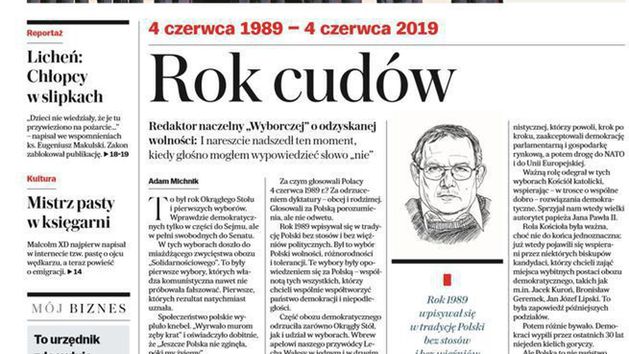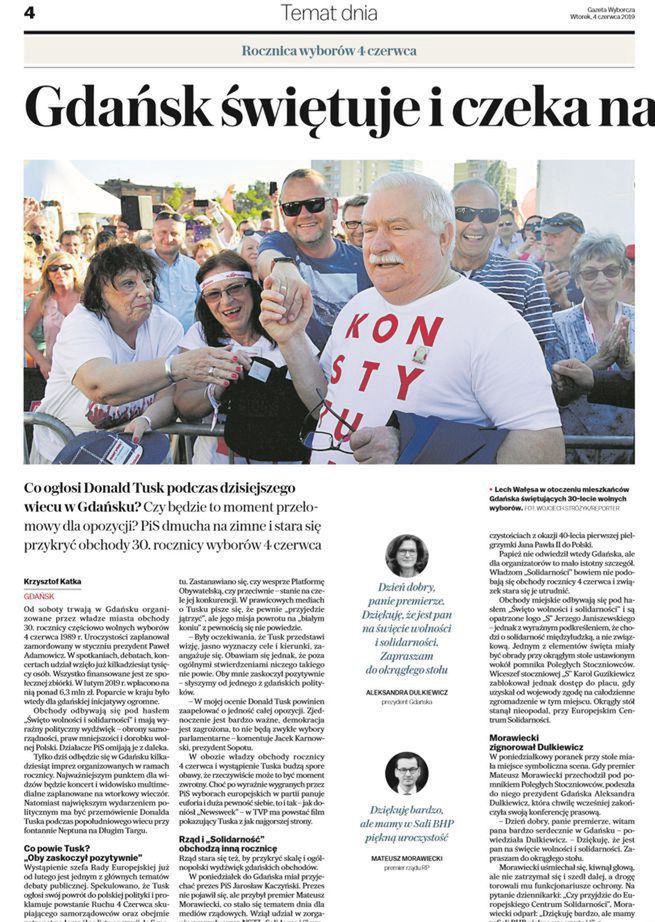
„Gazeta Wyborcza” świętuje w tym roku 30-lecie istnienia. W związku z tym odświeża makietę, której niemal nie zmieniała od 2006 roku. Nowy układ ma być nowoczesny, lżejszy i wprowadzać więcej „światła” na łamy. Zapewnić to m.in. nieco powiększona, prostsza czcionka, większe przestrzenie w projekcie poszczególnych stron oraz lepiej eksponowane fotografie, np. na drugiej stronie wydania. Dodatkowo autorzy komentarzy, felietonów i opinii będą przedstawiani rysunkowym portretem.
- W wymagających dla tradycyjnej prasy czasach nowa makieta wysokonakładowego dziennika to projekt wyjątkowy nie tylko na skalę polską. Zmiana układu i wyglądu wydań to znacznie więcej niż nowy projekt graficzny gazety – to także zmiana filozofii jej tworzenia oraz wyraźny, mocny sygnał, że wierzymy w nowoczesną, papierową „Gazetę Wyborczą” dopełniającą się z atrakcyjną ofertą cyfrową dziennika i dbamy o jej rozwój - mówi wydawca „Gazety Wyborczej” Jerzy Wójcik. - Nową „Wyborczą” ocenią oczywiście sami czytelnicy, ale jesteśmy przekonani, że jutro dostaną do ręki gazetę nowoczesną i klasyczną jednocześnie, a przede wszystkim przejrzystą i piękną.
Pojawią się „Temat dnia” i „Zdjęcie dnia”
Nowością będzie też „Temat dnia” - wyróżniony i najważniejszy zdaniem redakcji temat, który ma się przewijać przez kilka stron wydania dziennika. Obudowywany będzie różnorodnymi formami, np. komentarzami odredakcyjnymi, cytatami czy opiniami gości.
Na stronie drugiej gazety pojawi się natomiast „Zdjęcie dnia” - najważniejszy (zdaniem fotoedytora i wydawcy dziennika) kadr z poprzedniego dnia, obrazujący istotne wydarzenia w kraju lub na świecie.
Na dalszych stronach wprowadzonych zostanie sporo elementów dodatkowych - mniejszych form (jak komentarz czy rysunek), które będą miały za zadanie wspierać i obudowywać tematy wydania.
Nowa makieta ma być nowoczesna, dynamiczna, a wrażenie takie sprawiać będą m.in. tzw. rozkładówki, na których będą opierały się poszczególne strony. Wyraźniej graficznie będzie też zaznaczony główny temat każdego działu - tak by rzucał się w oczy czytelnikowi od pierwszej chwili, gdy ten przegląda gazetę (eksponowane miejsce, większy tytuł).
Druga część wydania to działy Opinie, Kultura, Nauka i Reportaż, w których więcej będzie dłuższych form dziennikarskich. Codziennie, oprócz sobót, na łamach dziennika pojawi się sekcja Poradnik, która będzie oferować praktyczne treści, użyteczne dla czytelników, np. informatory o zmianach w prawie, systemie emerytalnym bądź związane z edukacją. W czwartki Poradnik będzie miał charakter konsumencki, a w piątki zajmie cztery strony i w całości zostanie poświęcony tematyce zdrowotnej, zastępując wydania „Tylko Zdrowie”. W nowej makiecie zmieni się także wygląd tygodników „Duży Format”, „Ale Historia”, „Mój Biznes”, „Nasza Europa” i „Magazyn Świąteczny”.
Projekt makiety przygotował Jacek Utko, którego poprzednie projekty pięciokrotnie zdobywały nagrodę World’s Best Designed Newspaper i trzykrotnie European Newspaper of the Year.
- „Gazeta Wyborcza” będzie mieć szatę graficzną premium, odpowiednią do jakości swoich treści. Chciałem, aby jej makieta była bardziej spójna, by wszystkie sekcje i tygodniki wyglądały jak z jednej rodziny. Oczywiście, „Wyborcza” powinna też być nowoczesna i używać nowoczesnych rozwiązań graficznych, ale z konserwatywnym rysem, charakterystycznym dla prasy wysokiej jakości - wyjaśnia Utko.
Lokalne magazyny łączą się z „Co Jest Grane”, pojawiają się jedynkowe newsy
Od 7 czerwca zmienią się także lokalne wydania weekendowych magazynów „Gazety Wyborczej”. - Dzisiaj na okładkach dominują portrety. Nowy layout okładek da redaktorom większa swobodę i umożliwi lepszą ekspozycję tematów newsowych - mówi portalowi Wirtualnemedia.pl Mikołaj Chrzan, szef lokalnych redakcji „Gazety Wyborczej”.
Jak się dowiadujemy, wydawca połączy piątkowe magazyny lokalne z „Gazetą Co Jest Grane” w jeden grzbiet we wszystkich wydaniach poza Warszawą. - W ten sposób powstanie jeden obszerny, kompletny tygodnik z wydarzeniami, częścią featurową (większe formy) oraz informacjami kulturalnym i innymi, związanymi ze spędzaniem czasu wolnego. Przywracamy też opiniotwórczy charakter stronie drugiej: będzie z komentarzami, lokalnymi recenzjami i listami. Strona ta będzie miała także unikalny projekt graficzny - komentuje Mikołaj Chrzan. Dodaje też, że przygotowania z redakcjami lokalnymi obejmują nie tylko prace nad wdrożeniem nowego wyglądu stron, ale także wybór podejmowanych w piątki tematów.
Lokalne magazyny „Gazety Wyborczej” zmieniły się ostatnio w marcu ub.r. Zyskały wtedy nowe makiety, logotypy i tytuły, a na „jedynkach” pojawiły się portrety lokalnych bohaterów. Ostatnia strona była przeznaczona na rubrykę satyryczną. Zmiany miały służyć zdynamizowaniu wydań.
Zmiany zaprojektował Jacek Utko
To, że na 30-lecie wydania pierwszego numeru pojawi się nowa makieta, „Gazeta Wyborcza” zdradziła już w grudniu 2018 roku. Za projekt odpowiada Jacek Utko, który pracował nad nim od kilku miesięcy.
Utko projektował już szaty graficzne dla kilkudziesięciu dzienników na świecie m.in. dla „De Morgen”, „Het Parool”. W 2018 roku dziennik „Financieele Dagblad" otrzymał nagrodę konkursu graficznego European Newspaper Award za makietę zaprojektowaną przez polskiego grafika.